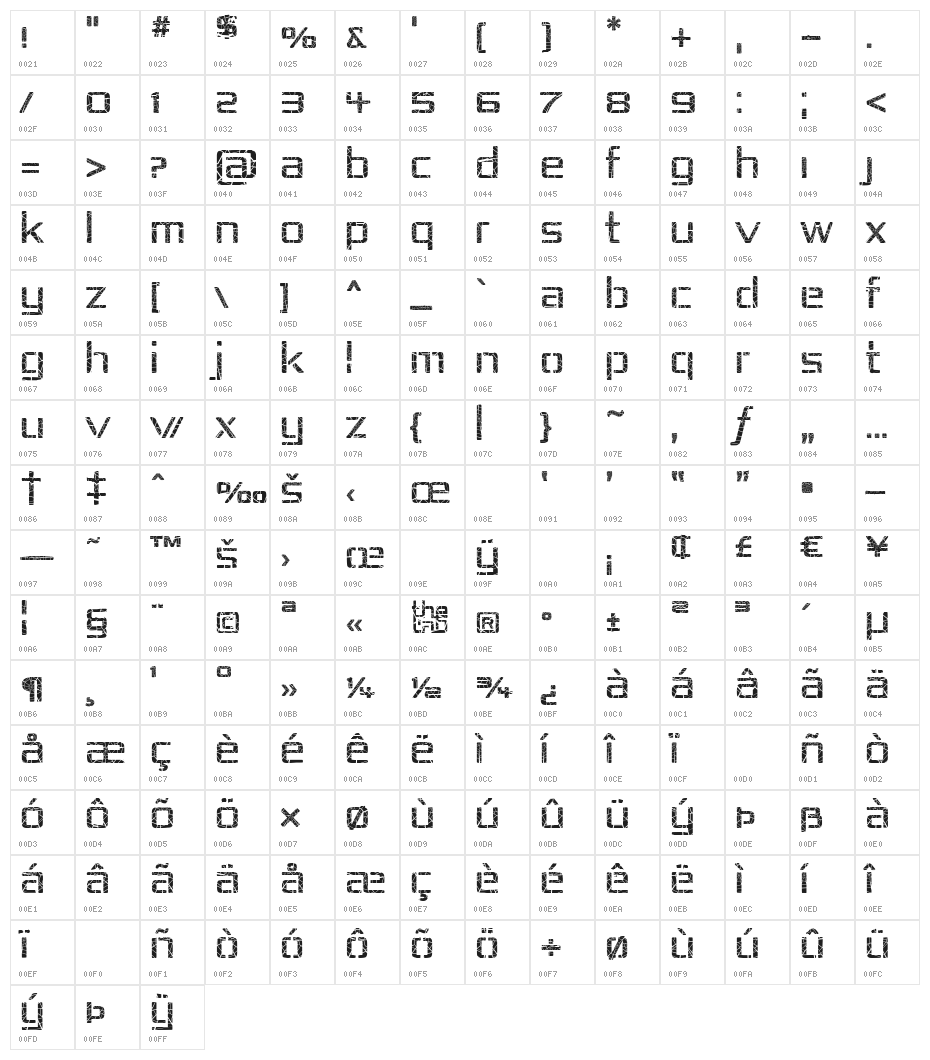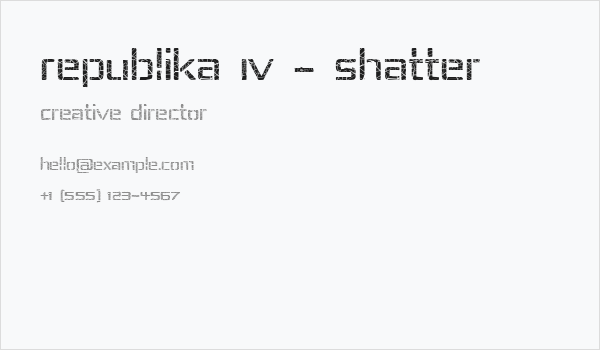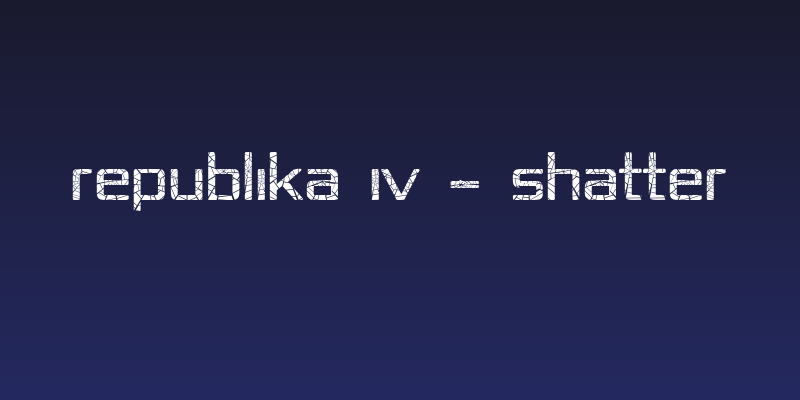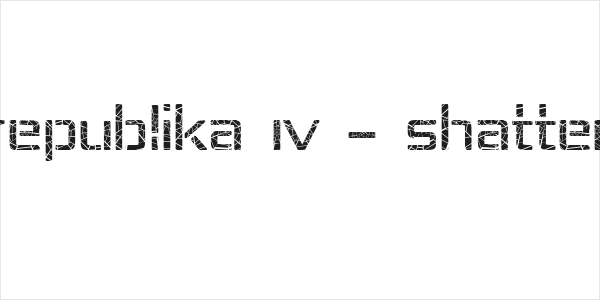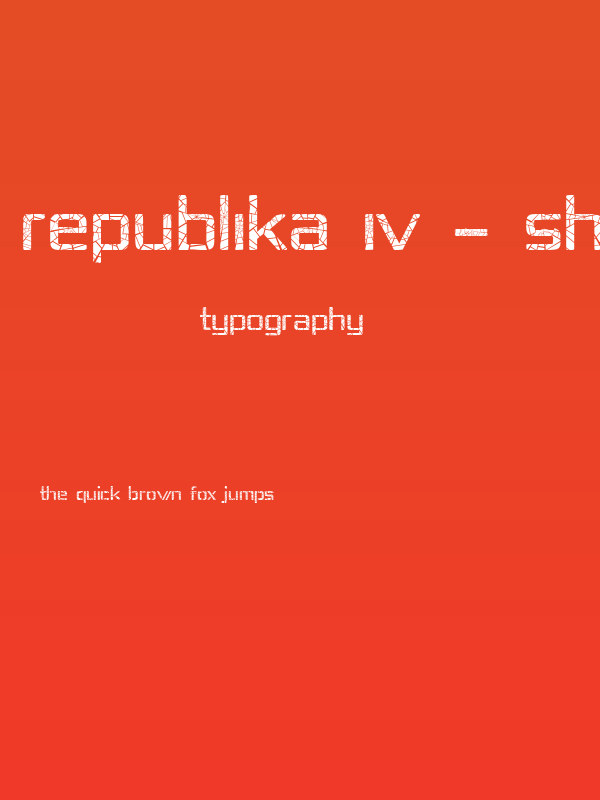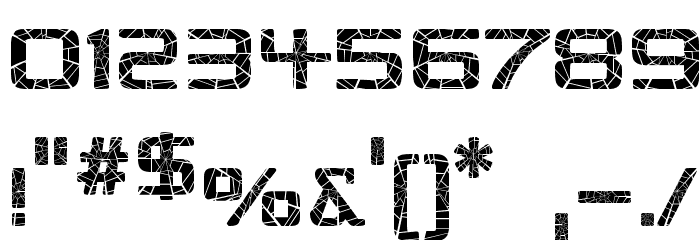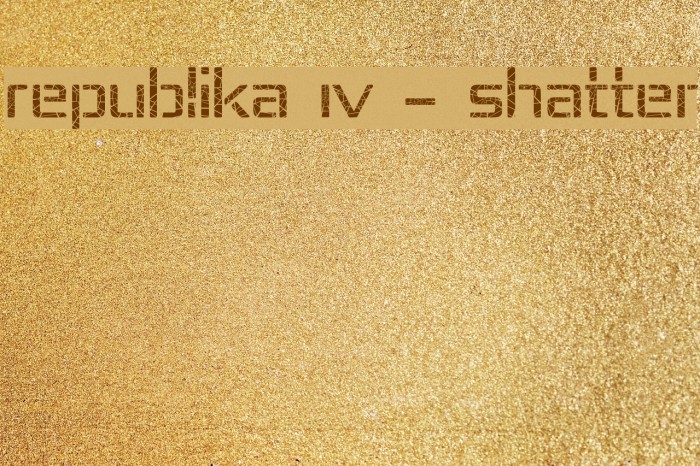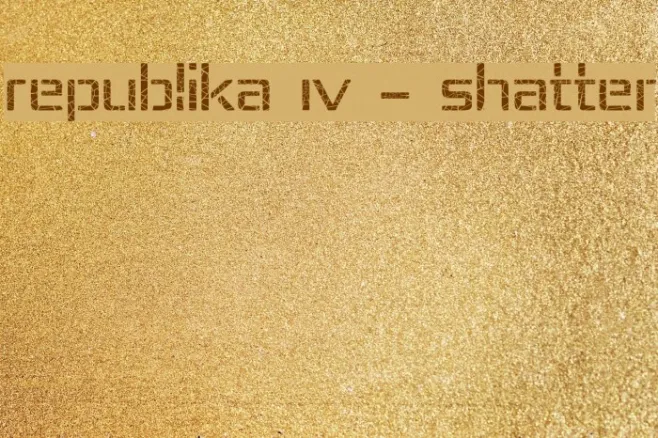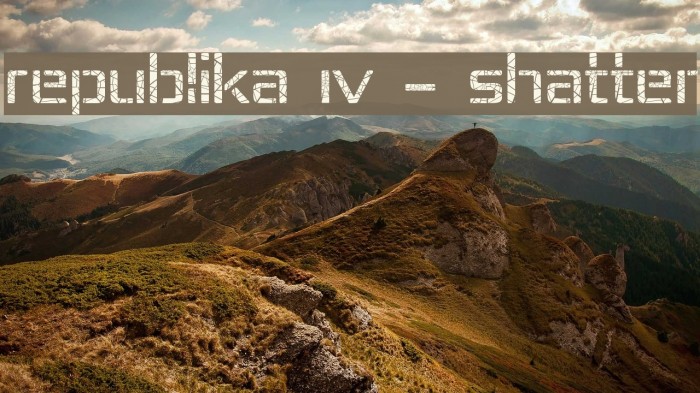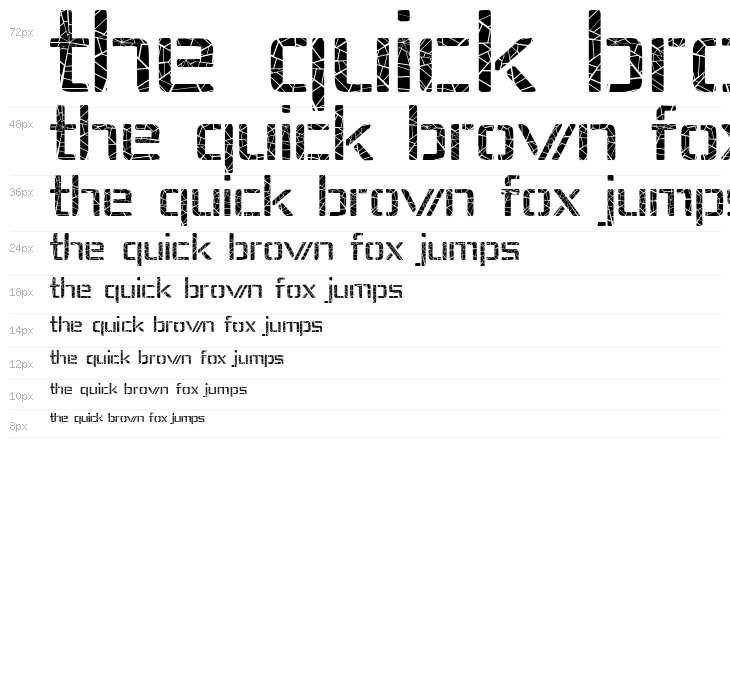
Republika IV - Shatter Font
| Stile generale | Modern, Decorative |
| Progetti proposti | Ideal for album covers, posters, branding materials, and any design project that seeks a bold, edgy look. |